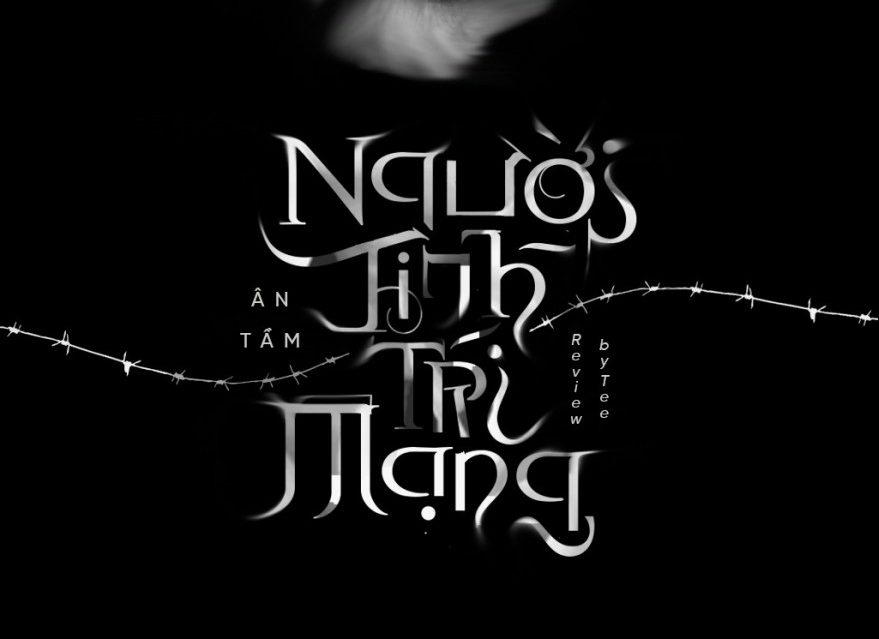
Giới thiệu về Font việt hóa MTD Volloa
Trong thế giới đồ họa hiện đại, việc tìm kiếm một Font việt hóa MTD Volloa chất lượng là điều mà bất kỳ nhà thiết kế nào cũng mong muốn. Đây là một bộ Font Miễn Phí mang phong cách Serif cổ điển nhưng vẫn giữ được nét thanh thoát, hiện đại và vô cùng sang trọng. Được đội ngũ MTD chăm chút kỹ lưỡng về dấu tiếng Việt, bộ chữ này đảm bảo sự liền mạch và thẩm mỹ tuyệt đối cho mọi sản phẩm truyền thông của bạn.
Tại sao nên sử dụng Font việt hóa MTD Volloa?
Thiết kế tinh tế và chuyên nghiệp
Font việt hóa MTD Volloa sở hữu các đường nét thanh mảnh kết hợp cùng các chân chữ sắc sảo, tạo nên một tổng thể hài hòa và đẳng cấp. Nó cực kỳ phù hợp cho các dự án thiết kế bìa sách, tạp chí, thiệp mời đám cưới hoặc nhận diện thương hiệu thời trang cao cấp. Khả năng hiển thị rõ nét trên cả màn hình kỹ thuật số và bản in giúp người dùng dễ dàng truyền tải thông điệp một cách ấn tượng nhất.
Khả năng ứng dụng linh hoạt
Không chỉ dừng lại ở các thiết kế cổ điển, bộ font này còn có thể biến hóa đa dạng trong các poster phim hoặc tiêu đề blog cá nhân. Sự cân bằng giữa tính nghệ thuật và công năng sử dụng giúp người mới bắt đầu cũng có thể tạo ra những tác phẩm đẹp mắt mà không cần quá nhiều kỹ năng phức tạp.
Hướng dẫn sử dụng và kết luận